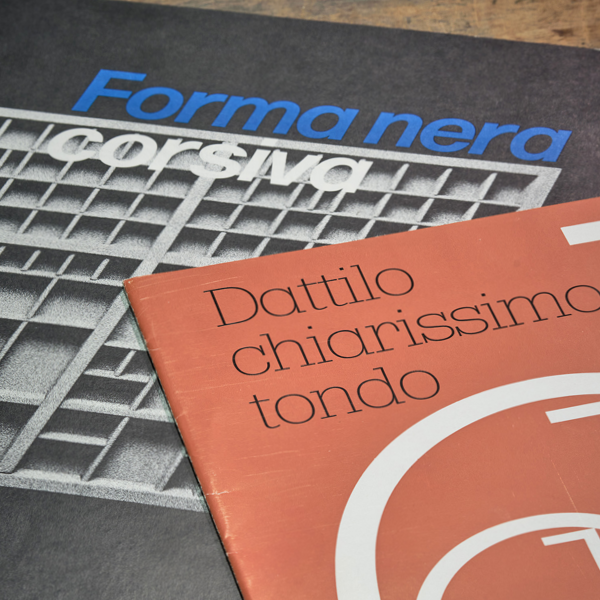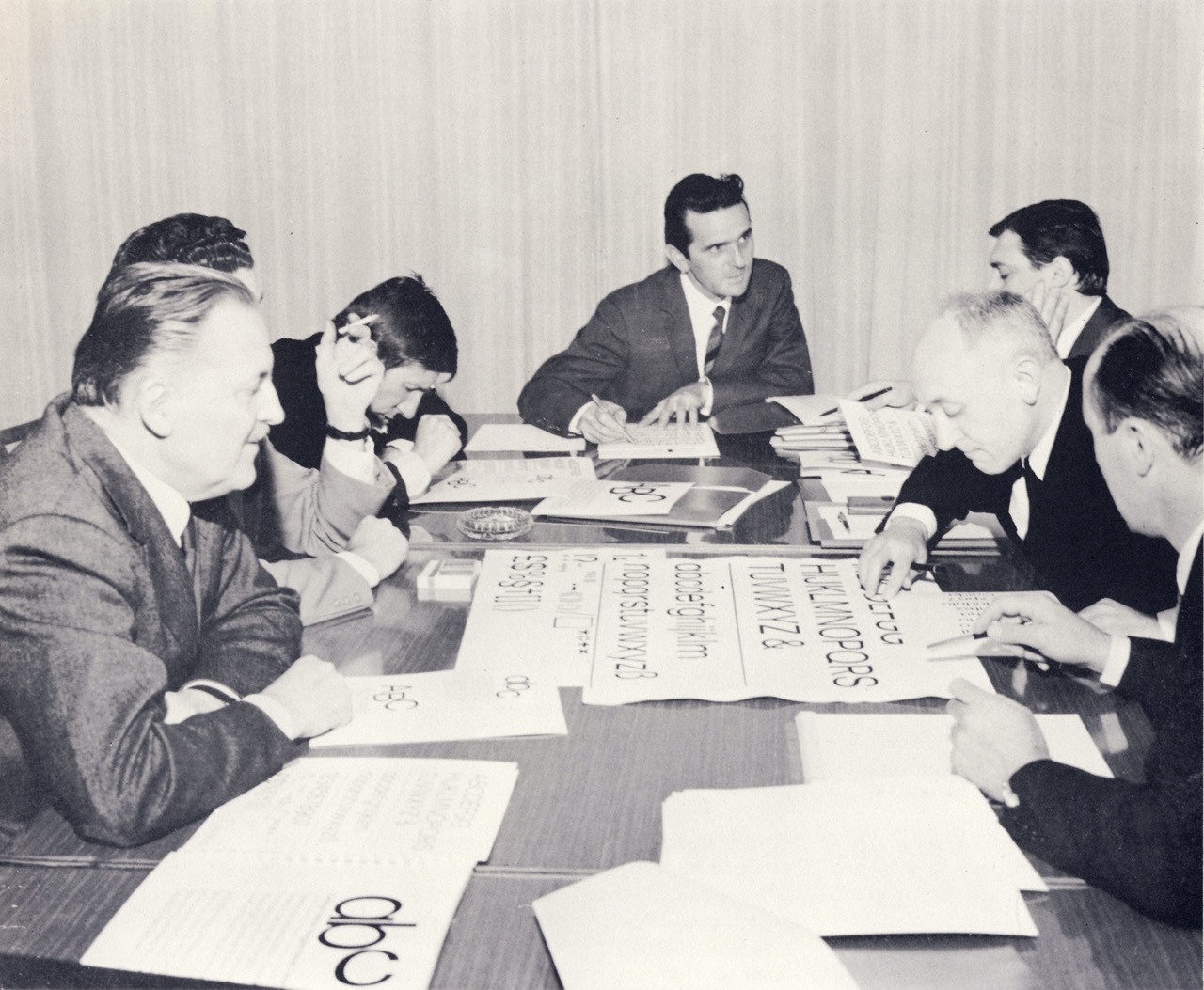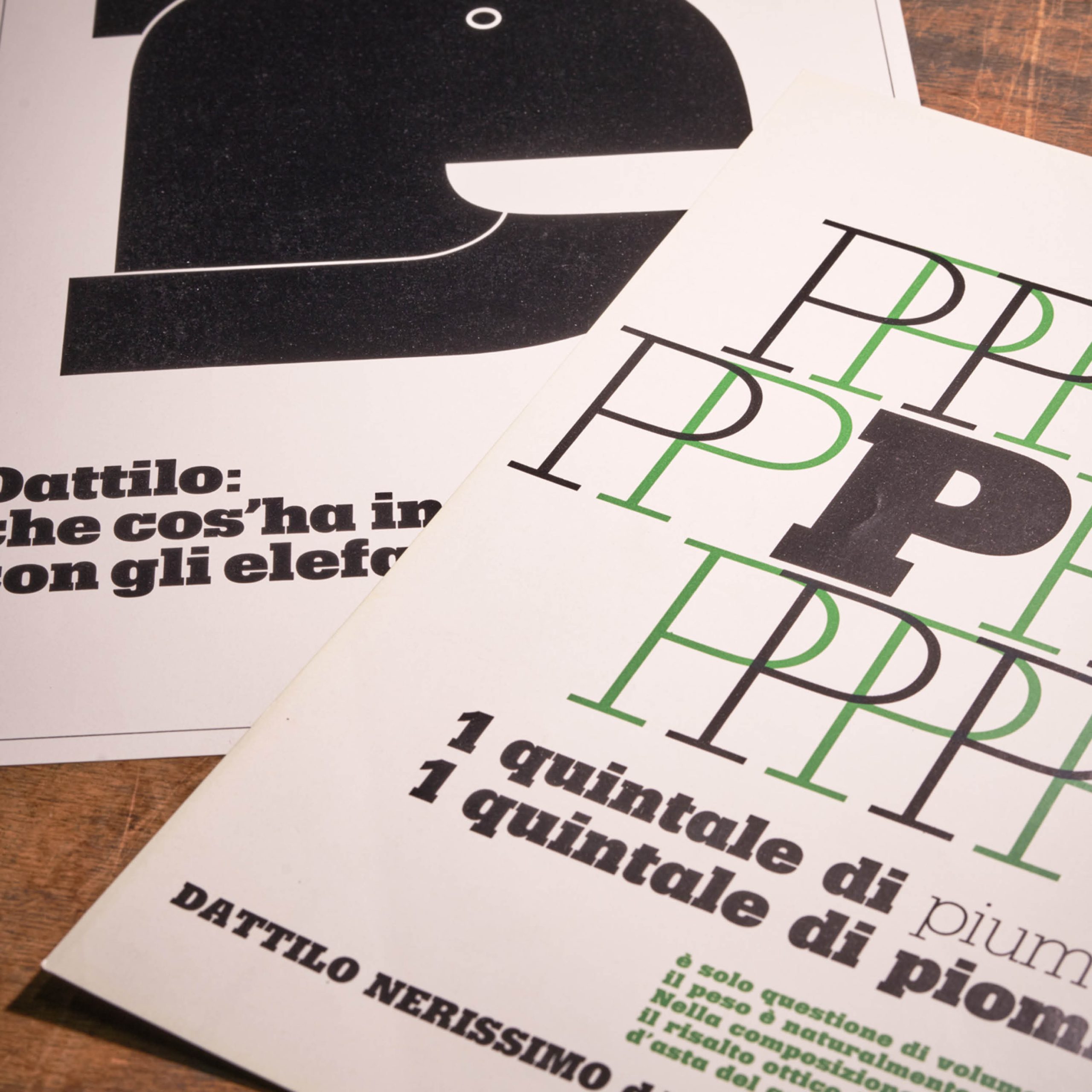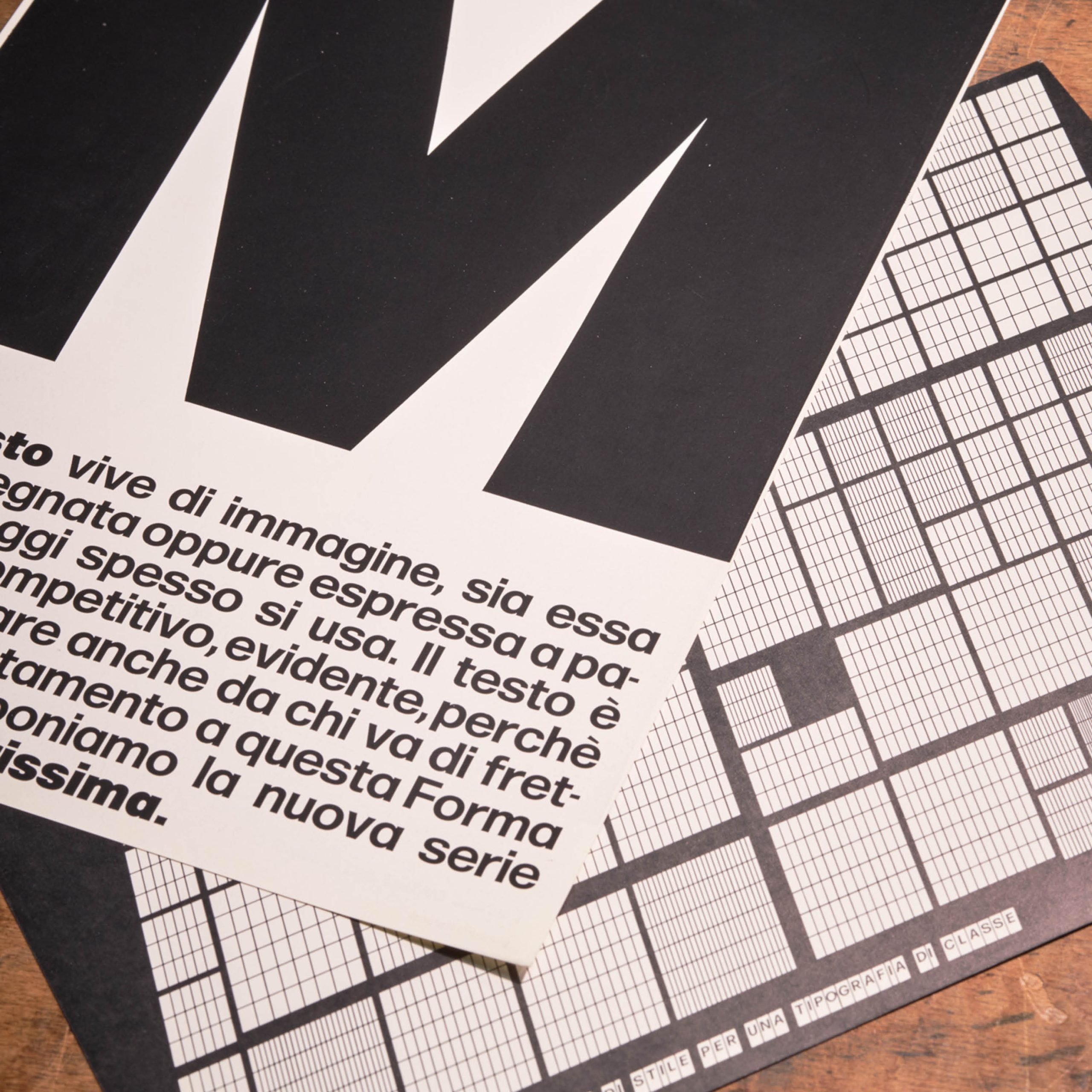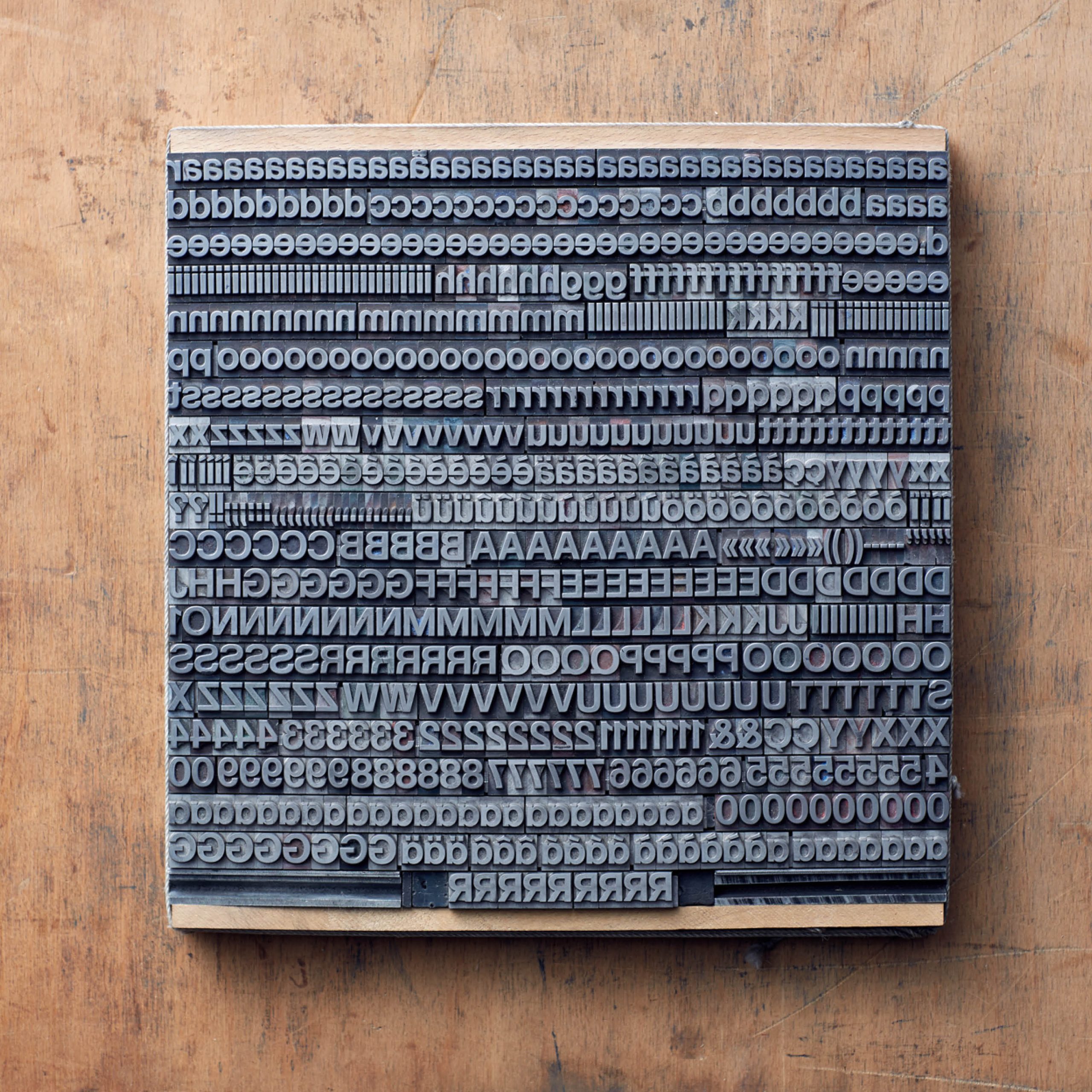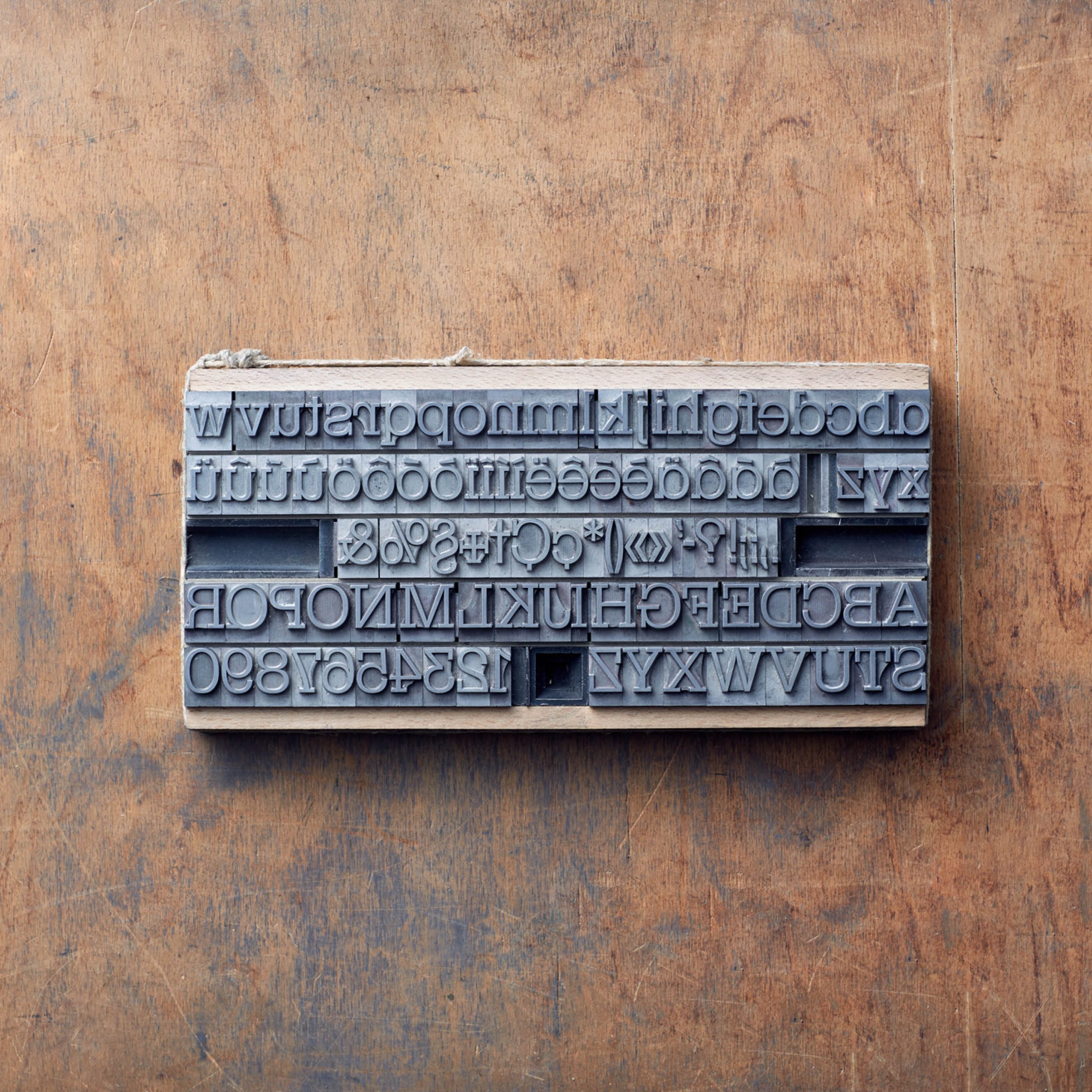
Dattilo e Forma: design di squadra
Gli ultimi anni della carriera di Aldo Novarese come direttore dello Studio Artistico Nebiolo, videro la progettazione di due caratteri “anomali”, nella loro genesi, rispetto alla tradizione dell’azienda torinese: il Forma e il Dattilo. Per il disegno di questi tipi, la Nebiolo scelse di affiancare a Novarese un gruppo di grafici (dal 1965 al 1973) che potessero supervisionare e indirizzare l’operato dello Studio Artistico. Furono coinvolti alcuni dei nomi più importanti di quel periodo, provenienti da Milano, centro italiano per la grafica fin da inizio ’900. Il team era composto da grandi professionisti: Pino Tovaglia, Franco Grignani, Giancarlo Iliprandi, Bruno Munari, Ilio Negri, Till Neuburg e Luigi Oriani. Il compito principale di questa unione tra Novarese e i grafici milanesi era di dare vita a quello che avrebbe dovuto essere il nuovo lineare italiano, ovvero il Forma, sulla scia della tendenza europea dettata dall’Helvetica. Il team lavora sul Forma negli anni 1965-66 e sul Dattilo nel 1972. Per questi due caratteri i grafici contribuirono sia al disegno dei glifi che alla comunicazione su carta stampata, attraverso la progettazione di campionari e brochure pubblicitarie.